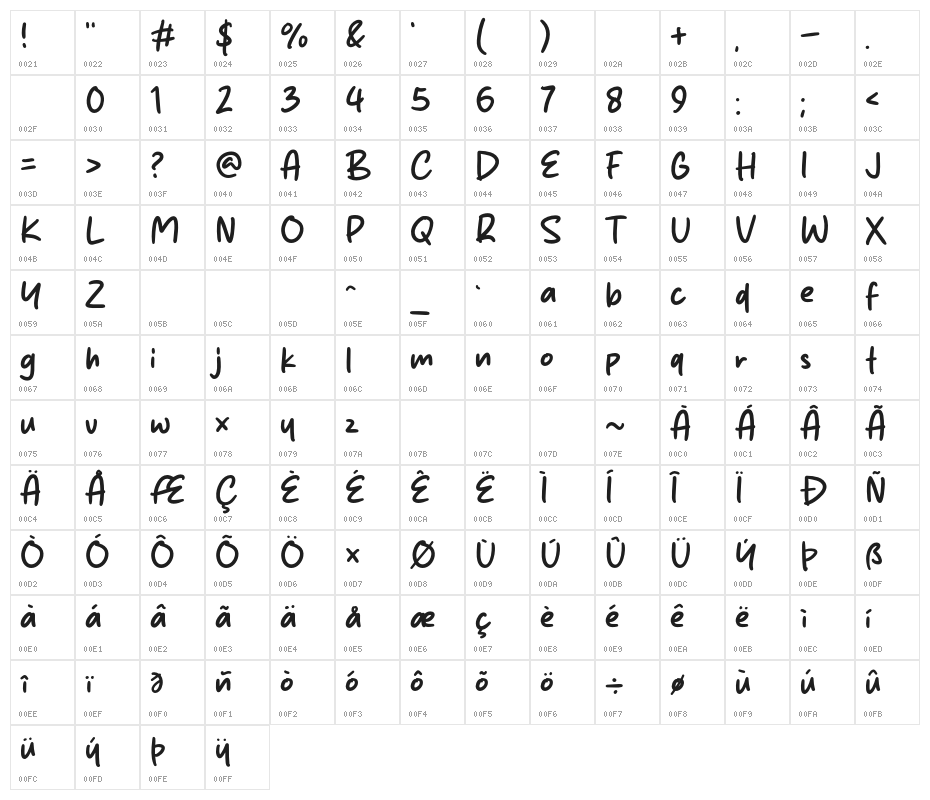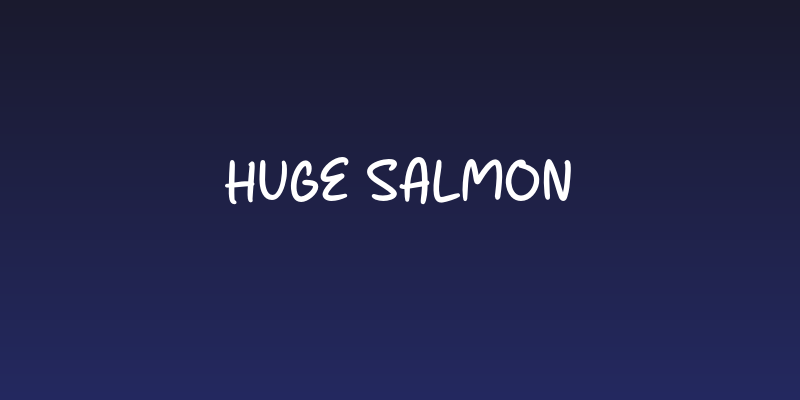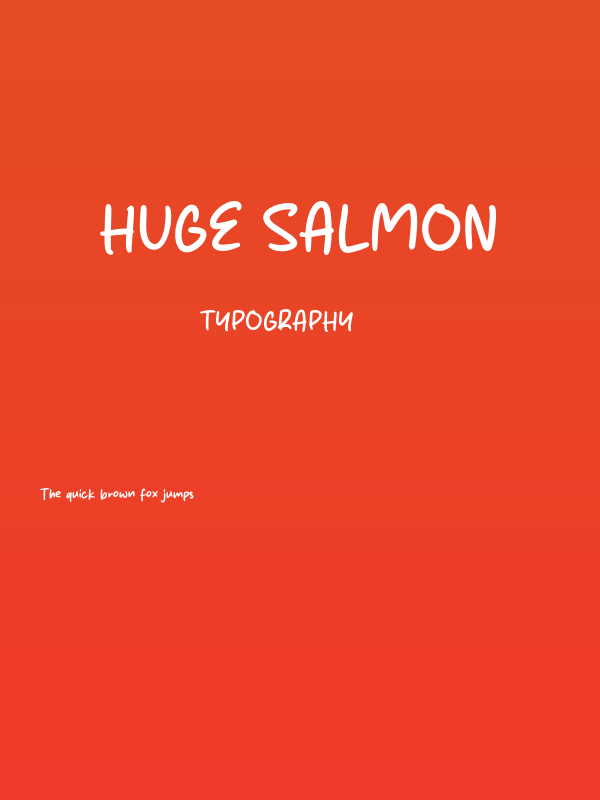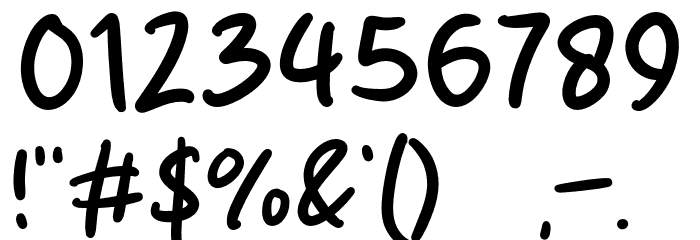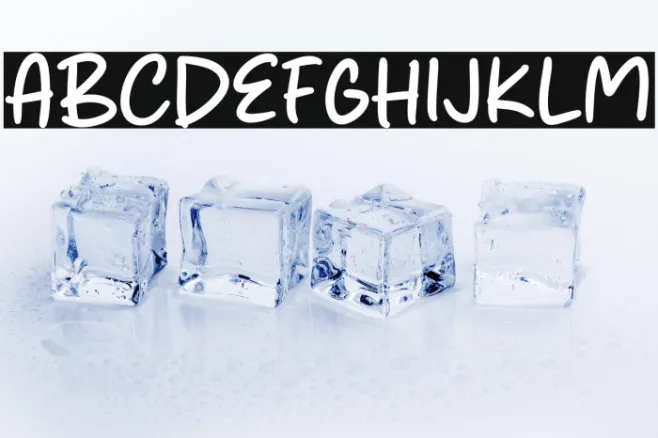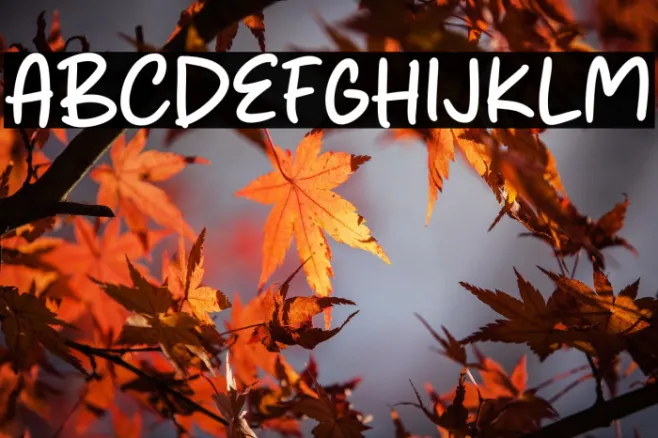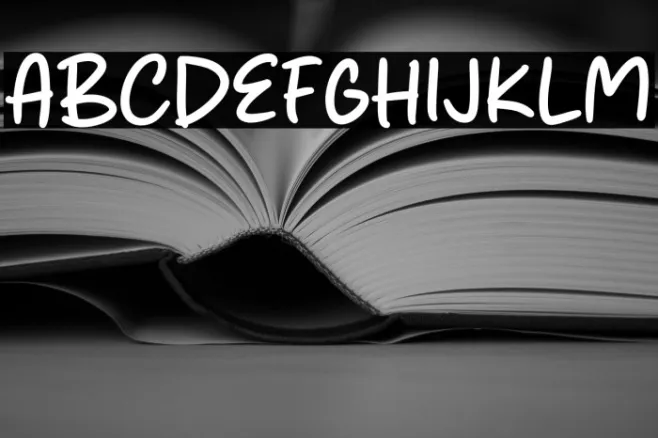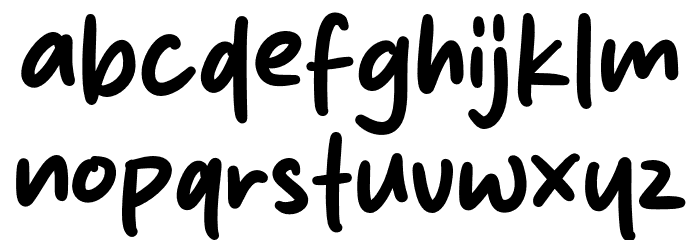
Huge Salmon Font
| Gesamtstil | Casual |
| Anwendungsfall | Headlines, Informal text, Personal projects |
| Vorgeschlagene Projekte | Ideal for greeting cards, personal blogs, informal invitations, and children's books. |